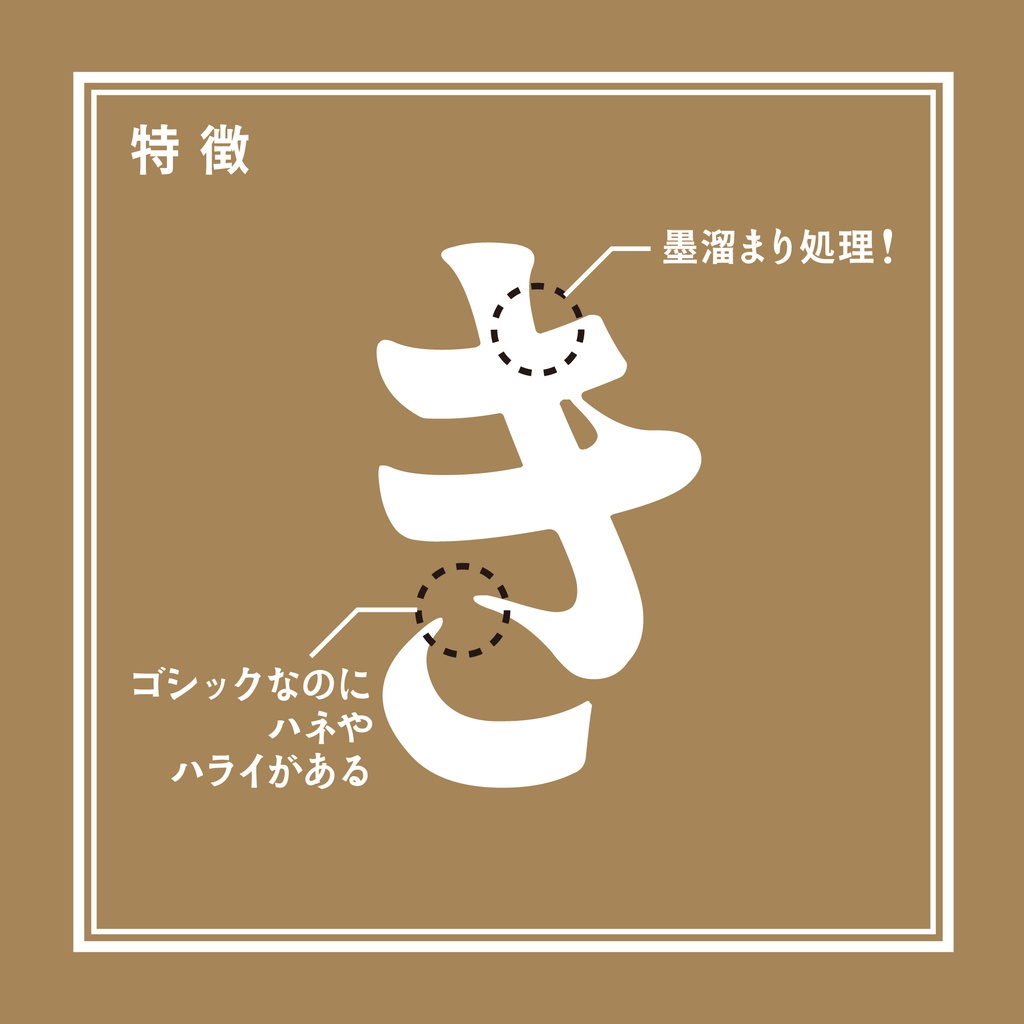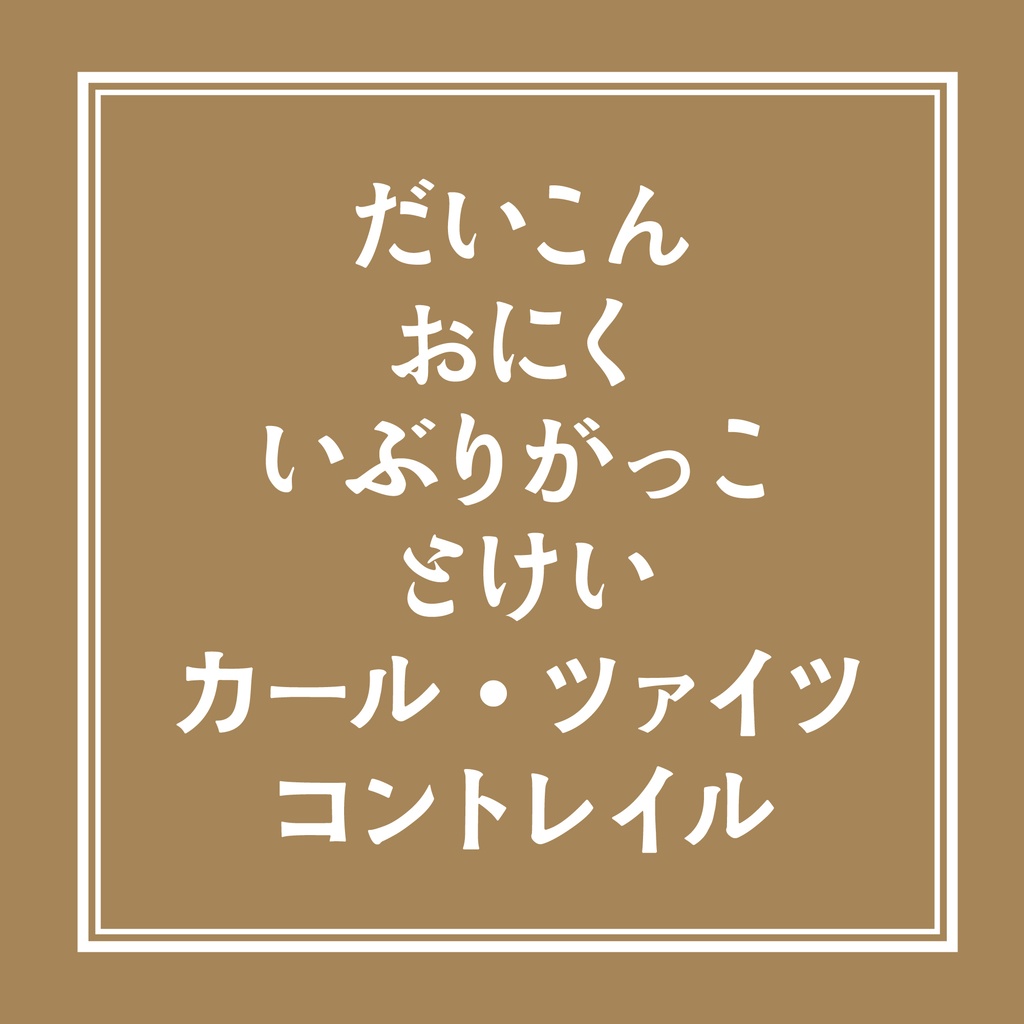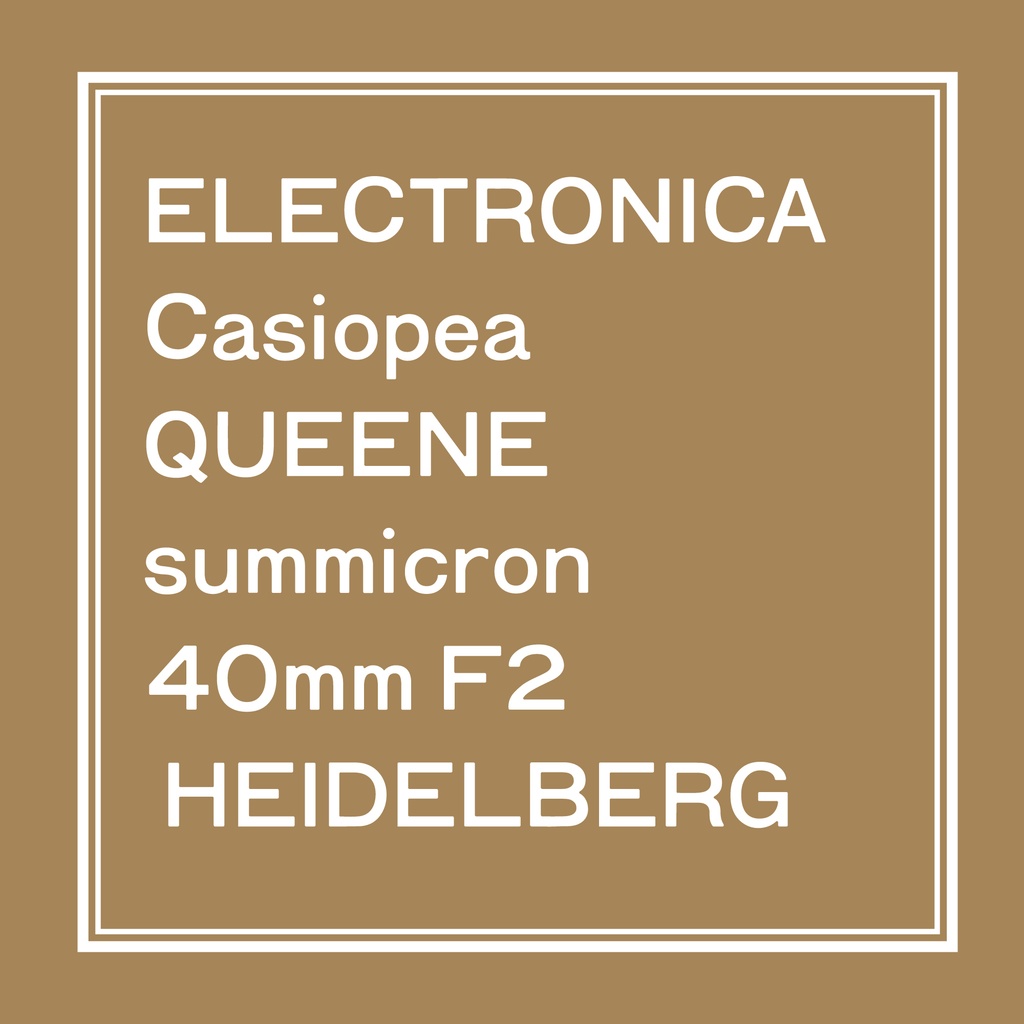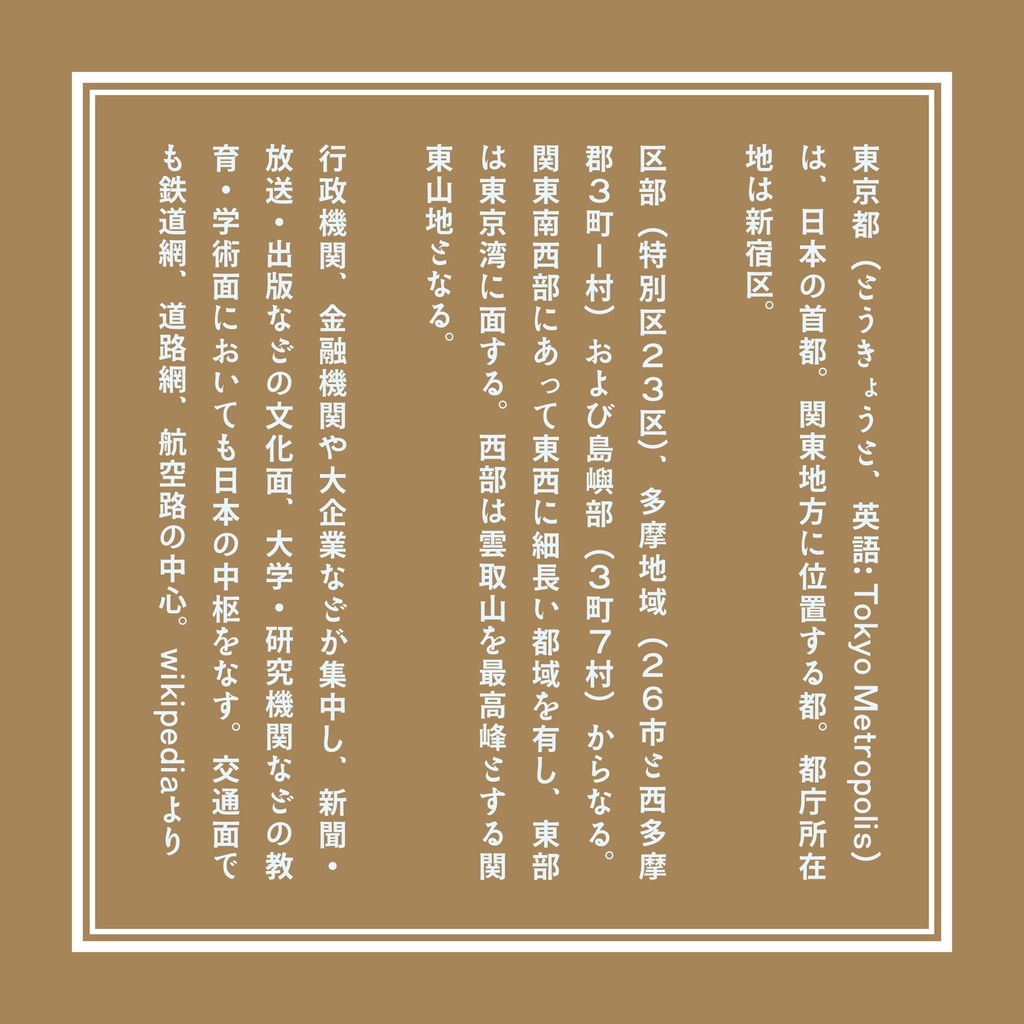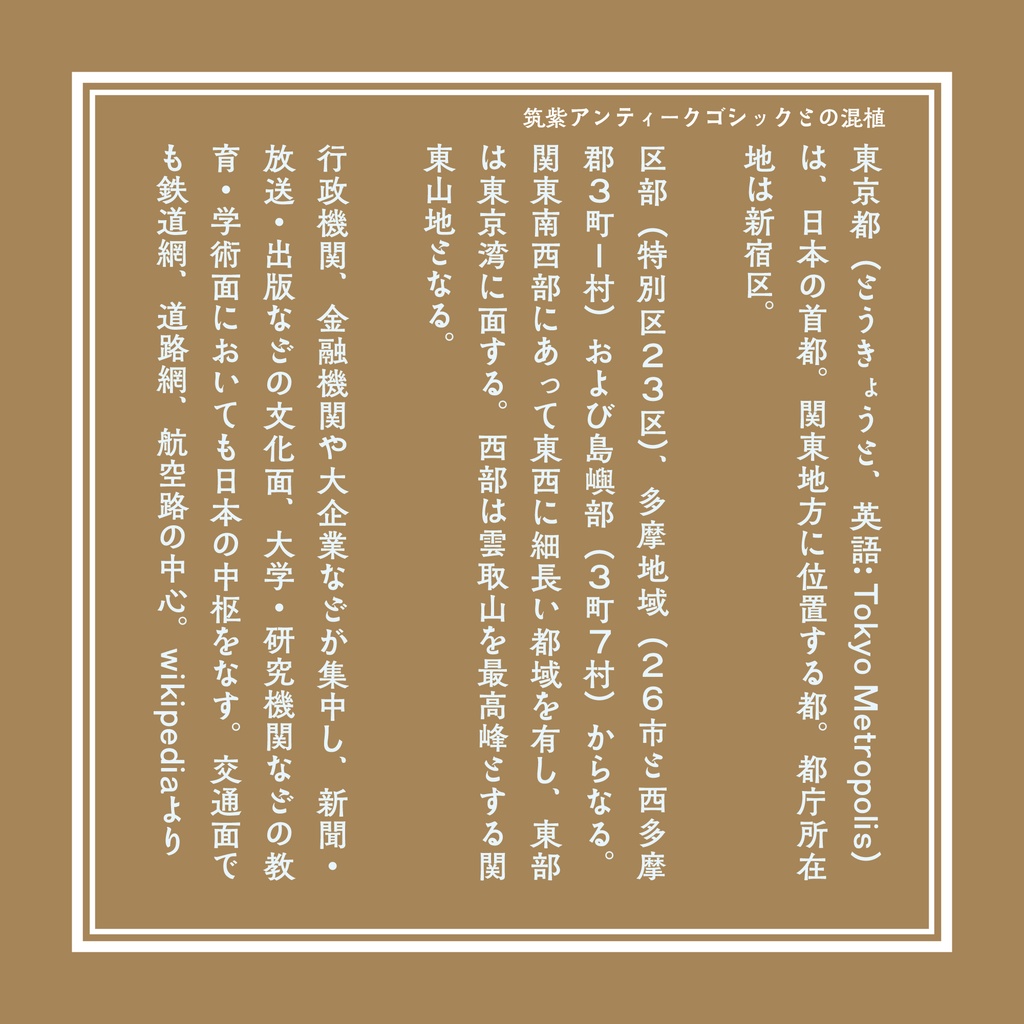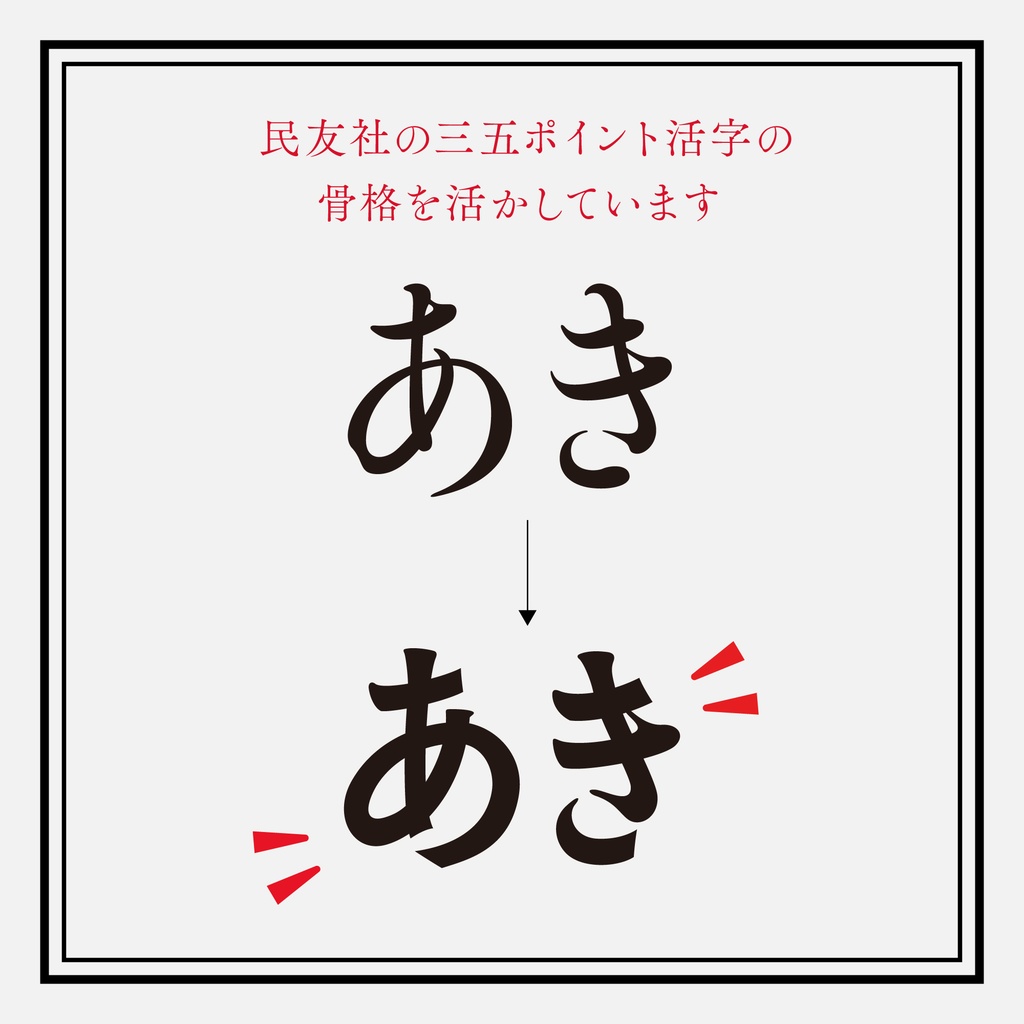
【フリーフォント】「築豊35ポイントゴチック」オールドスタイルのゴシック
■書体概要
このフォントは架空の活字書体「築地35ポイントゴチック」があったらをテーマにしています。かな骨格は民友社三十五ポイント明朝(築地の三十六ポイント系)を参考にしています。今までありそうでなかったオールド系ゴシックで、元の豊かな筆脈と筆勢をなるべく残すようにしています。欧文は写植のときによく見たバランスが独特なやつが元です(伝われ)。全体的に軽く墨溜まりかけてあります。
かなと一部約物、アルファベットを除き源ノ角ゴシックの派生フォント「源石ゴシック」から利用しています。